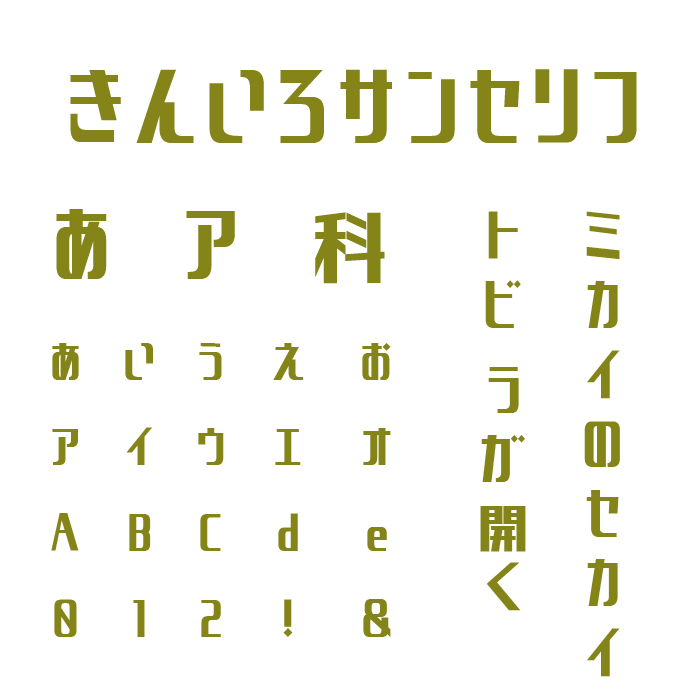
きんいろサンセリフ
「きんいろサンセリフ」フォントは、人気4コマ漫画およびアニメ『きんいろモザイク』のタイトルロゴをヒントに制作されたデザインフォントです。
縦に長い長体変形が特徴で、文字のはらいが力強く、インパクトを感じさせるフォントデザインになっています。
文字に力があるフォントなので、タイトルやロゴ、見出しなど、きんいろサンセリフフォントを利用することで、目を引くビジュアルを作り出すことができます。Youtubeのサムネイルデザインや動画テロップなどにもおすすめです。
きんいろサンセリフフォントの文字組見本
きんいろサンセリフ
収録文字は、ひらがな、カタカナ、数字、記号、英数字、漢字が3448文字程度を収録されています。